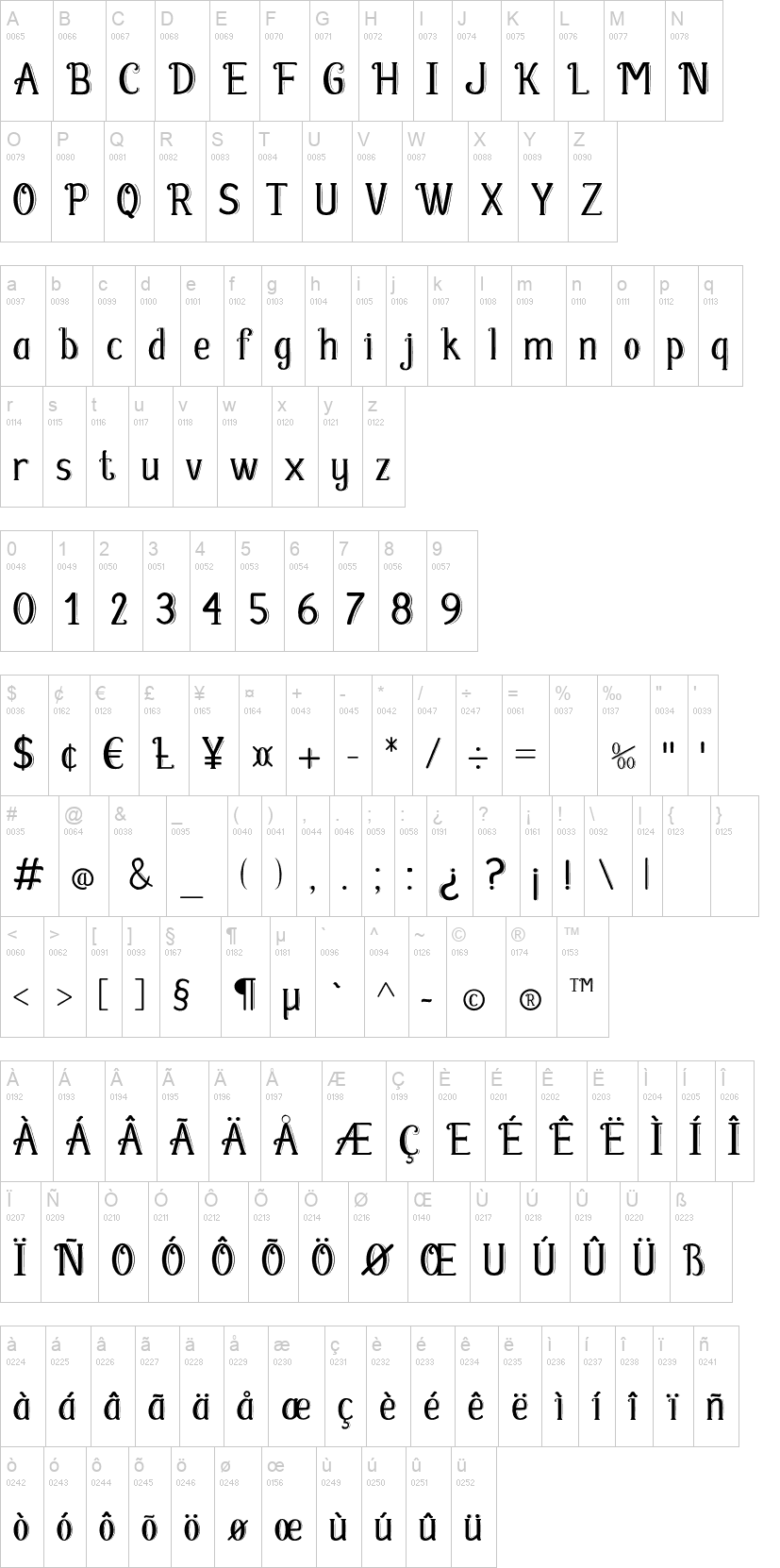
Note of the authorFabula es una tipografía creada para ser usada para títulos de cuentos (específicamente en los de fantasía, novelas de romanticismo,etc.) para niños y jóvenes.
Inspirada en los la tipografía de los Títulos de los cuentos de los hermanos Grimm y en los Clásicos de Disney.